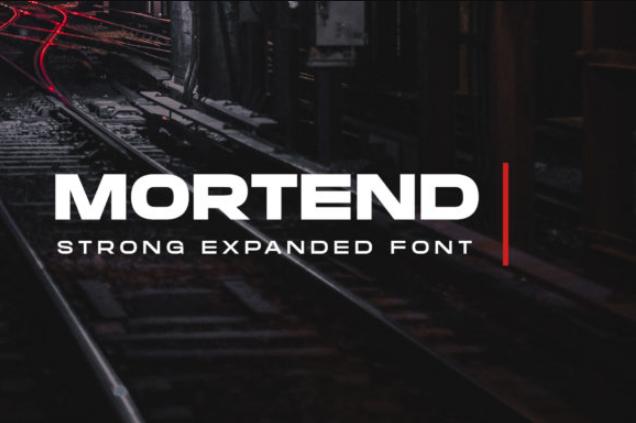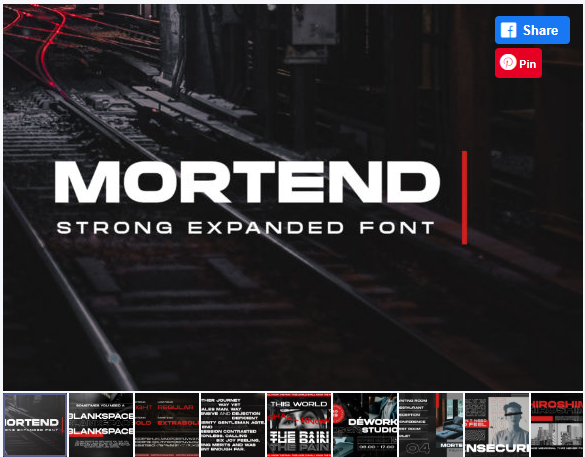
[Creativefabrica] Mortend Font (Arterfak Project)
Mortend - это смелый и футуристический шрифт без засечек. Мастерски разработанный, чтобы стать настоящим фаворитом, этот шрифт может воплотить каждую вашу творческую идею на высшем уровне!